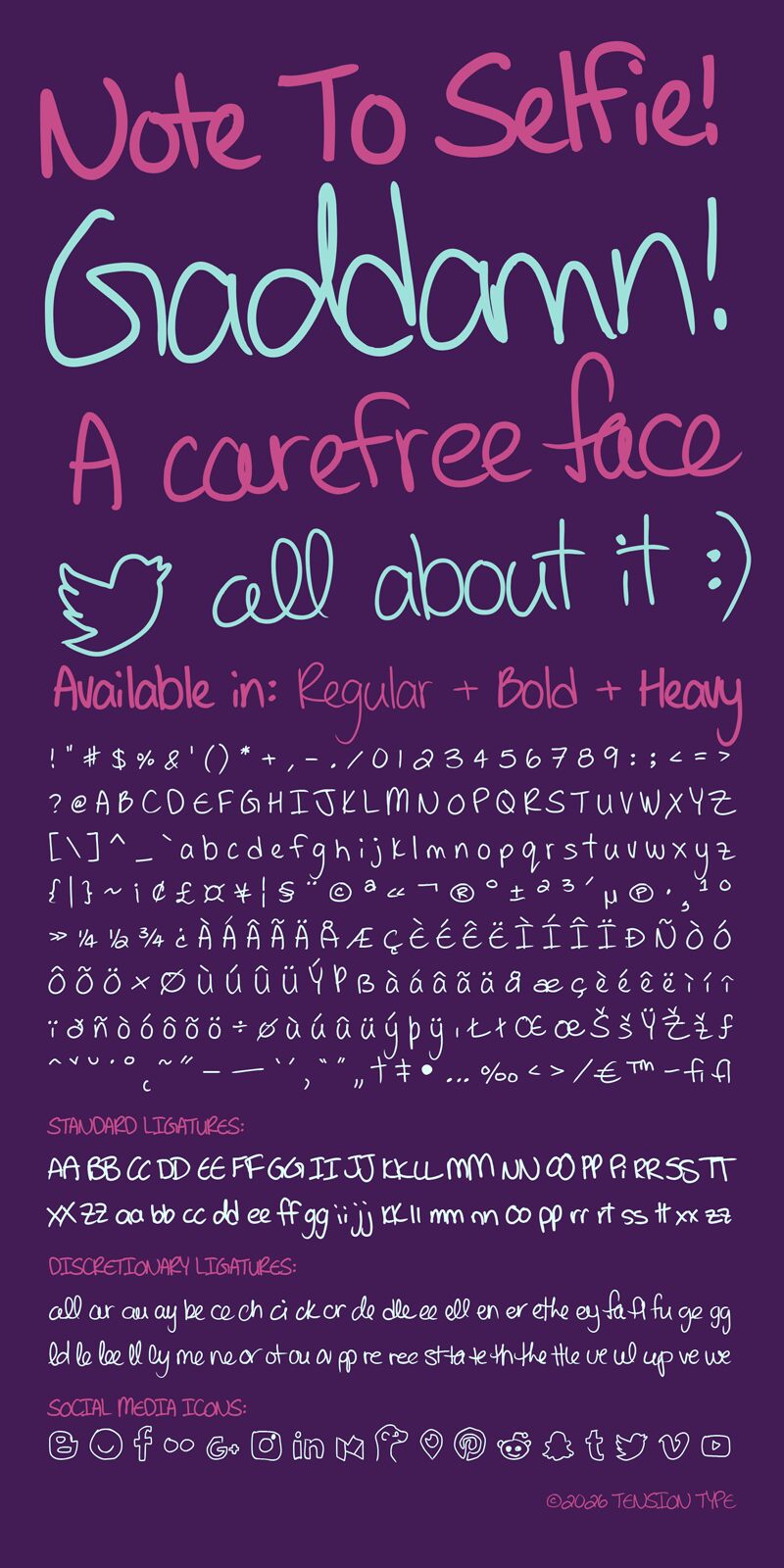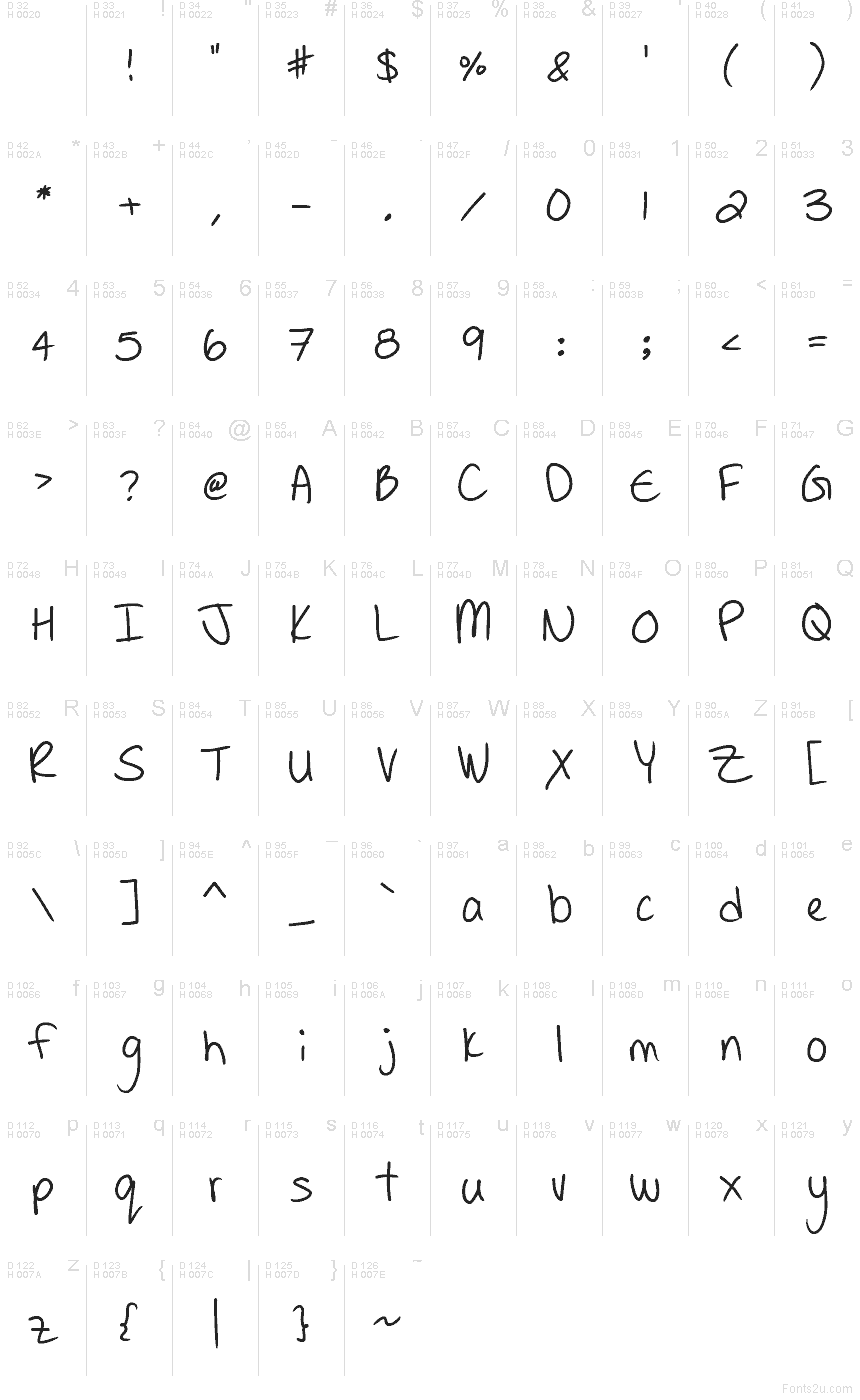
Note to Selfie Bold di Tension Type è un carattere scritto a mano gratuito che imita il ritmo rapido delle note prese con un pennarello. Grazie ai suoi tratti alti, alle asole e alle curve rilassate, mantiene uno stile disinvolto senza apparire disordinato. Questo ritmo costante di scrittura a mano le conferisce l’autenticità di un vero appunto, ricordando più un messaggio sul frigorifero o un’annotazione in un’agenda che una calligrafia studiata.
È perfetta per grafiche social, citazioni in stile diario, biglietti d’auguri, packaging a tema scolastico e titoli per scrapbook, dove questa qualità di «nota volante» aggiunge un tocco intenzionale. Anche titoli brevi, adesivi e didascalie traggono beneficio dal suo stile arrotondato tipico del pennarello, che rende il tono personale anziché formale.
Un altro font scritto a mano tra cui scegliere. Potrà sembrare un po' scompigliato, ma ha un aspetto autentico. Non è un insieme creato tramite autotraccia; dietro c'è del lavoro vero. Spero che sia quello giusto per il tuo progetto.